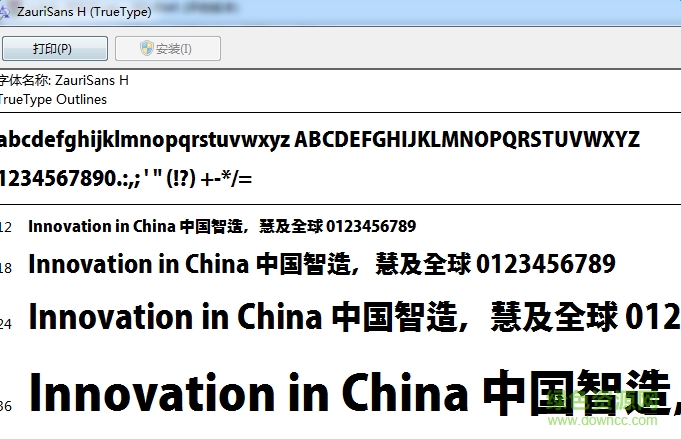
塚源黑體H
塚源黑體H字體是一款非常有個(gè)性的黑體字體,該字體可以廣泛應(yīng)用于廣告設(shè)計(jì)、宣傳海報(bào)、ppt、影視制作以及任何使用文字的領(lǐng)域,有需要的朋友可以免費(fèi)下載收藏。
塚源黑體H字體是一款個(gè)性字體,超粗的線條給人難以忘懷的感覺(jué),極具個(gè)性的排版,更是充滿魅力。有喜歡的朋友趕快來(lái)下載使用吧!